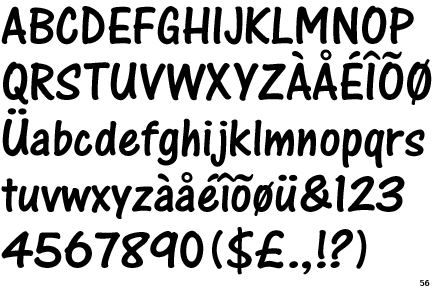
mein Tipp auf die Schnelle im Vorbeihuschen wäre:
One Stroke Script
A legibile brush-style typeface.
Designer: Paul Clarke
Year: 1984
Einsortiert und gefunden in meinem E-Katalog als Skript->Marker->Medium. Das ging nach zwei kläglichen Fehlschlägen mit Schriftensuchmaschinenen dann wesentlich schneller als die beiden vorherigen Fehlschläge.
Die sollte mal in die Liste mit Comic-Sans-Alternativen aufgenommen werden … ich kann bloß dort leider keine Kommentare hinterlassen, weil das System mich immer rausschmeißt … :-(
Als echte Comic-Sans-Substitute fallen mir folgende freie Schriften ein:
Gapstown AH http://www.dafont.com/de/gapstown-ah.font
KTF Dion  http://martinsilvertant.deviantart.com/art/Dion-Sans-277277174
Swagger http://www.dafont.com/de/swagger-kt.font
Ich würde aber lieber zu einem anderen Ansatz tendieren. Mein bevorzugter Ansatz wäre eine Seite mit Schriften für Comic-lettering.
Eine sehr gute Anlaufstelle ist Blambot mit kommerziellen und einigen freien Schriften und deren Rubrik "dialogue fonts":
Bei Fontsquirrel gibt es auch rund zwei dutzend freie Comicschriften in der Kategorie "comic":
Auch in der Kategorie "handdrawn" kann man fündig werden:
Bei Google-Fonts ist die Suche in der Kategorie "handwritten" angesagt:
Dazu könnten dann die sich hier Herumtreibenden noch ergänzende Daten von anderen (idR kommerziellen) Schriften liefern.
Dazu dann noch eine Seite für die Headlines ...
Da gibt es bei Blambot die Kategorie "Sound Effects Fonts":
und die Kategorie "Design Fonts"
Bei Fontsquirrel findet man einiges in der Kategorie "Humorous":
sowie der Kategorie "Casual":
die eine oder andere Schrift in der Kategorie "handdrawn":
und mindestens eine Schrift in der Kategorie "comic":
Bei Google-Fonts ist die Suche in der Kategorie "display" angesagt:
Noch ein paar ausgewählte, freie Schriften:
Einfach mal durchwühlen. Bzgl. kommerzieller Schriften müssten da die hier mit mir Ablungernden nachhelfen. Ich habe da nicht viel Kenntnisse und kann nur die üblichen Verdächtigen nennen: Bertam (Corel) ... Für exotische Überschriften dann die übliche Suche in den jeweiligen Kategorien von Dafont oder ähnlichen Seiten ... Asien  ... Russland/UdSSR ... Handgemalte Grotesk ...